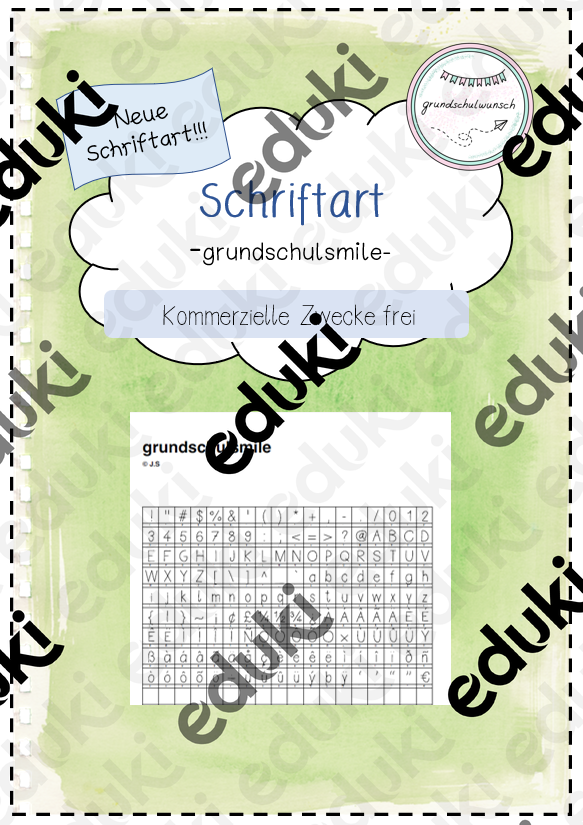
Neue Schriftart grundschulsmile
Schriftart grundschulsmile - kommerzielle Zwecke frei
Liebe grundschulwunsch, vielen Dank für diese wunderschöne und super lesbare Schrift! Ich benutze sie nur noch! :) Leider ist mir aufgefallen, dass die "Anführungsstriche unten" als Sonderzeichen fehlen. Könntest du die vielleicht noch hinzufügen? Das wäre grandios. LG Bine